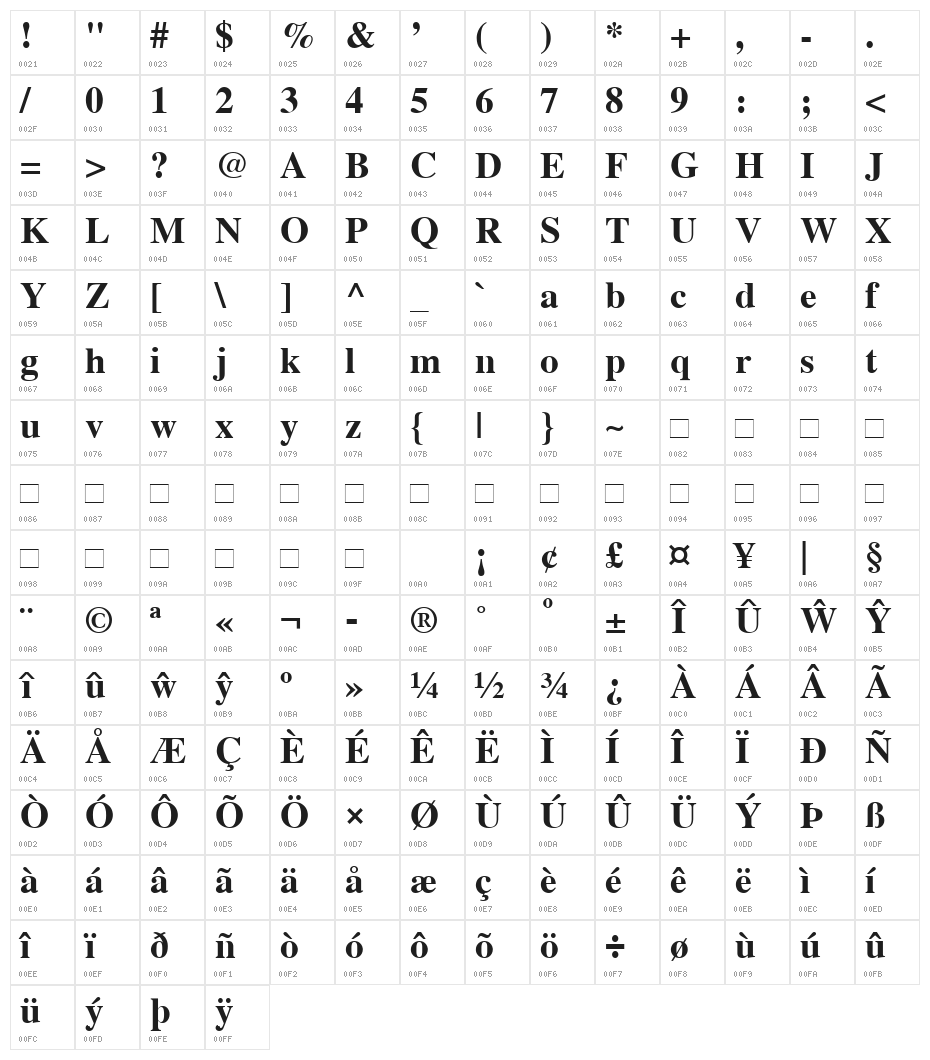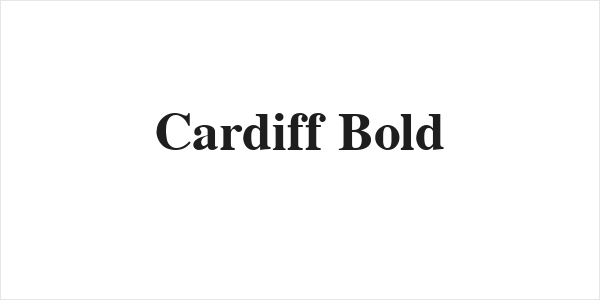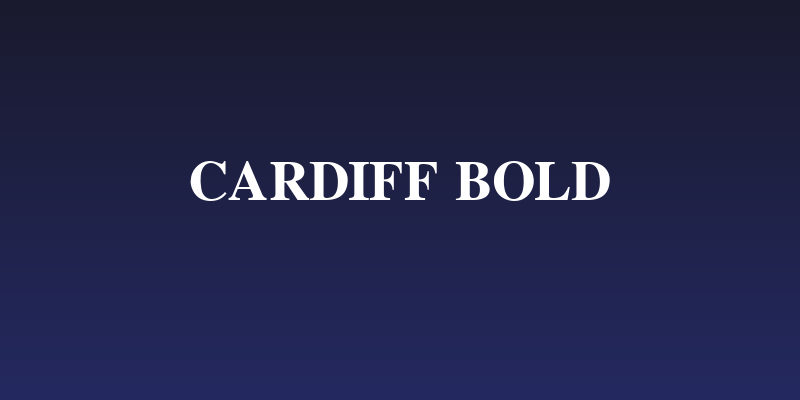
Cardiff Bold Font
✎ Serif
| समग्र शैली | Classic |
| उपयोग का मामला | Headlines, Logos, Editorial Design |
| सुझाए गए प्रोजेक्ट | This font is perfect for editorial design, book covers, branding projects, and any application requiring a strong, traditional presence. |